おしゃれなゆる筆記体♪文字見本の使い方
手帳やノートをちょっとおしゃれにしたいときに役立つのが「筆記体の文字見本」。
A〜Zのアルファベットや数字、記号、曜日や月名などがまとまっていると、どこからでも気軽に真似して書けます。
今回は、そんな文字見本の使い方やアレンジ方法をご紹介します。
【PDF】ゆる筆記体 見本帳 8Pミニブックができました、今回はこちらを使って文字見本の使い方をご紹介していきます。
よくある文字見本の内容
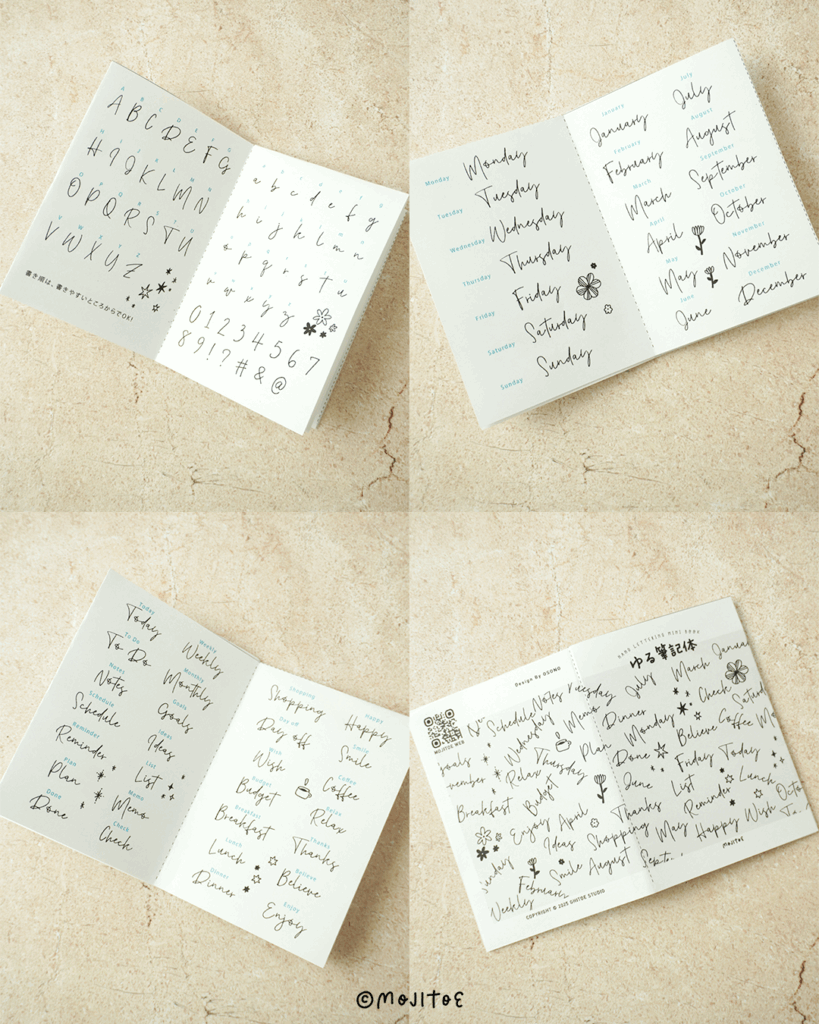
筆記体の文字見本には、次のようなものがそろっています。
- A〜Zのアルファベット単品
- 数字や記号
- 曜日や月名などのフレーズ
- TodayやWeeklyなどの手帳によく使うフレーズ
まずは眺めるだけでも「こういう形なんだ」と参考になります。
透かしてなぞって練習する
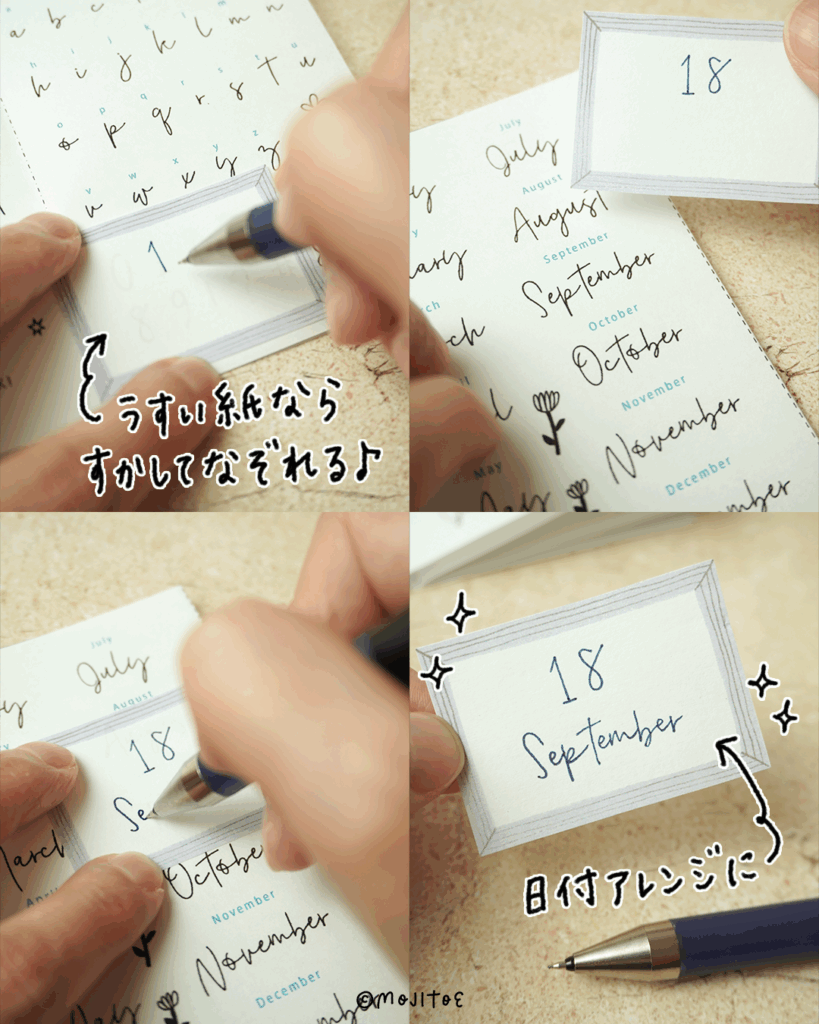
いきなり真似して書くのは難しくても、紙を重ねて透かしながらなぞればOK。
今回は、コピー用紙に印刷したミニメモ紙を上から重ねて使いました。
薄い紙を使えば、下の文字がしっかり見えてなぞりやすいですよ。
日付やタイトルにアレンジ
筆記体は、日付や見出しに取り入れると一気におしゃれ感がアップ。
たとえば「September」や「Mon」をサッと書くだけで、海外の雑誌のような雰囲気に。
おしゃれな筆記体の日付アレンジは、とても簡単に取り入れられます。
イラストを添えてかわいく
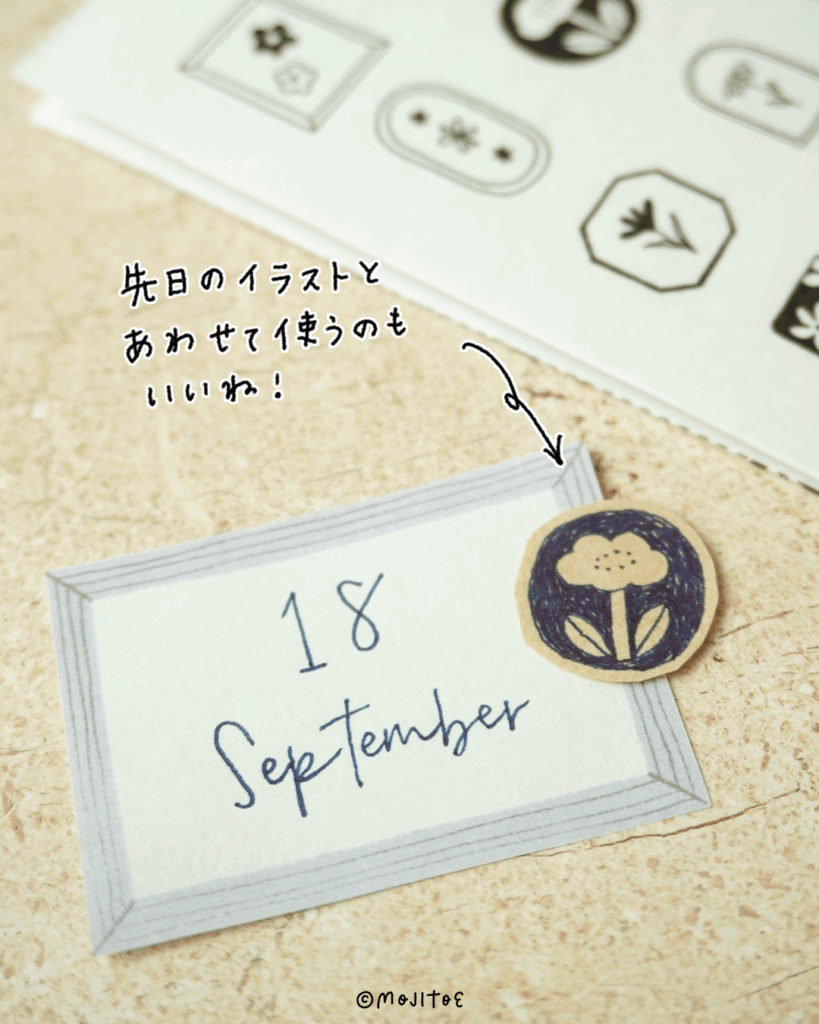
シンプルな筆記体に、小さなイラストを添えるとさらに映えます。
イラストは別紙に描いておき、切り抜いて貼ると失敗しても何度でもやり直せるのでオススメ。
文字とイラストの組み合わせは手帳デコの醍醐味です。
フレーズを組み合わせる
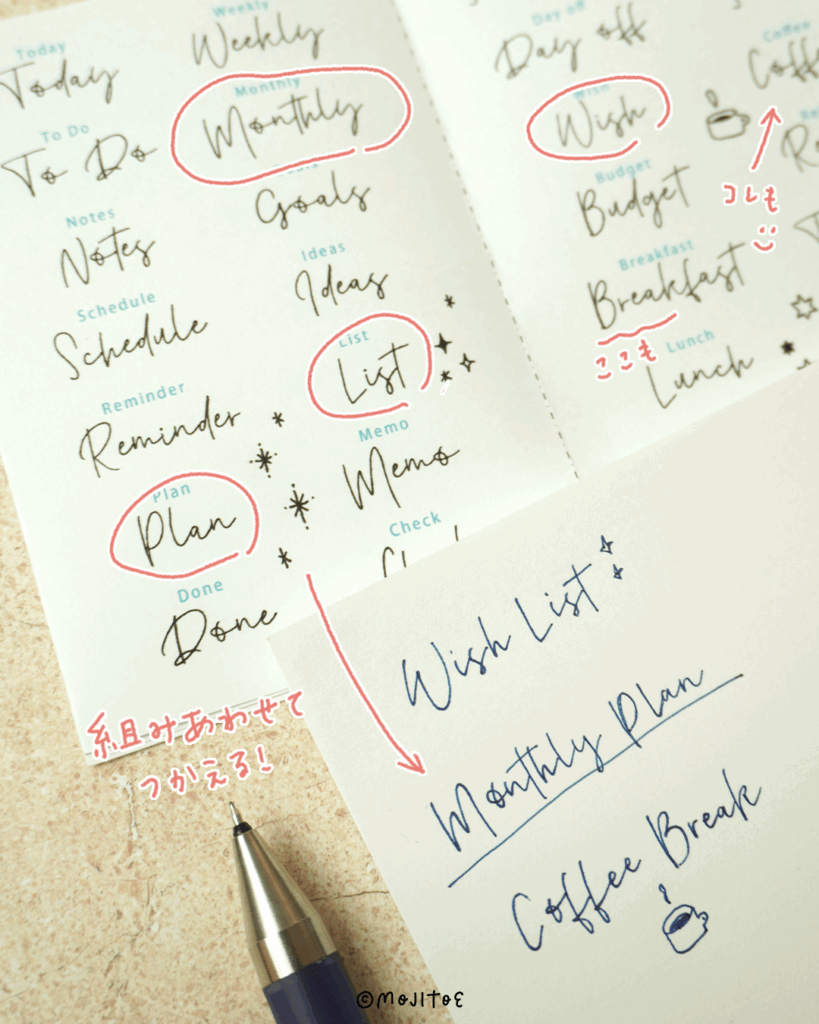
文字見本にそのまま欲しいフレーズが載っていなくても大丈夫。
単語を組み合わせて自分だけのフレーズにアレンジできます。
たとえば「Wish」と「List」を組み合わせて「Wish List」に。
パーツ感覚で自由に組み合わせると、使える幅がぐんと広がります。
今週の目標ページ見本です。見出しに筆記体で「Weekly Goals」と書きました。
自分らしい筆記体を手帳に加えれば、毎日の記録がもっと特別になります。
見本を上手に使って、ちょこっと取り入れて楽しんでみてくださいね。